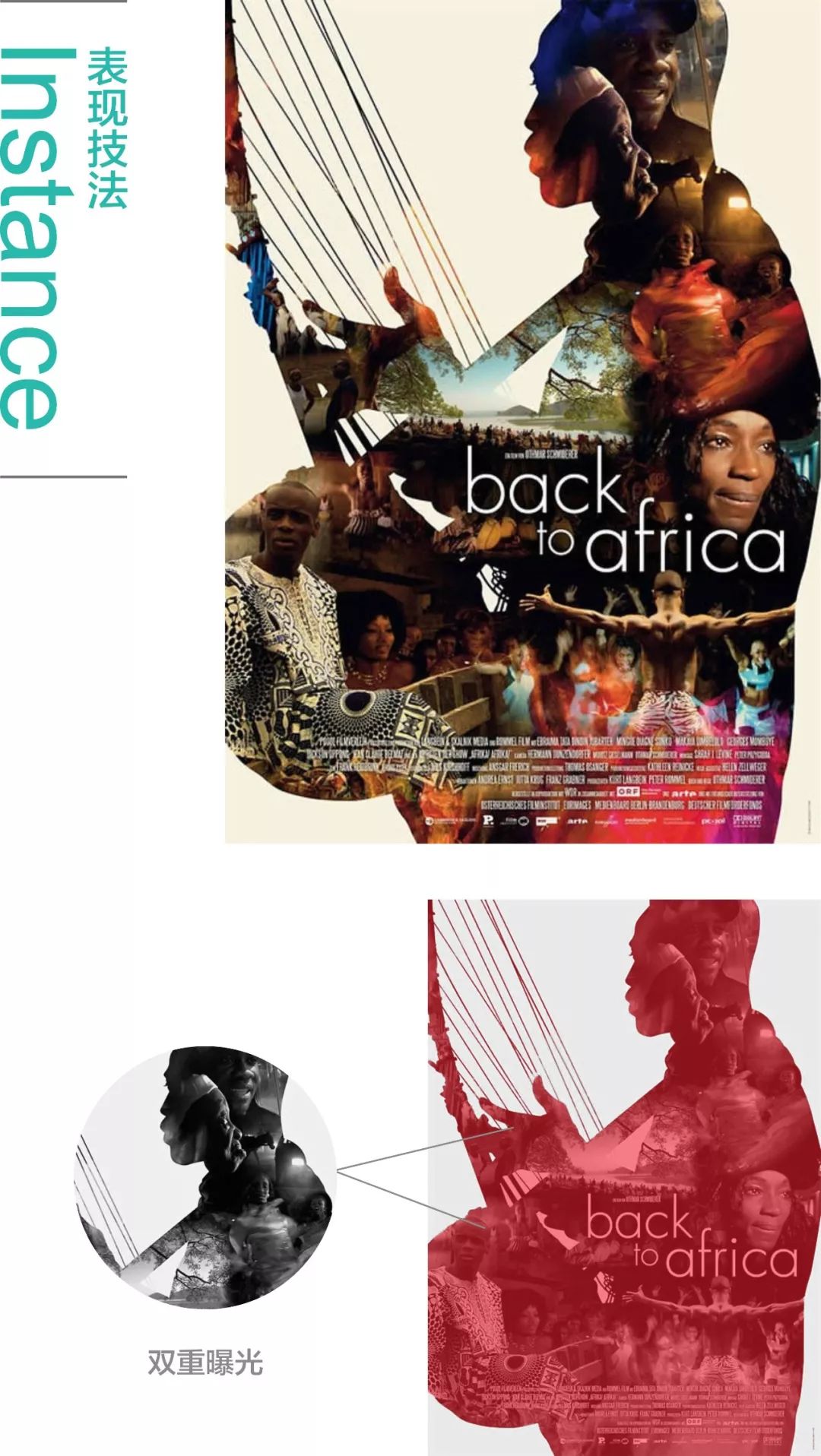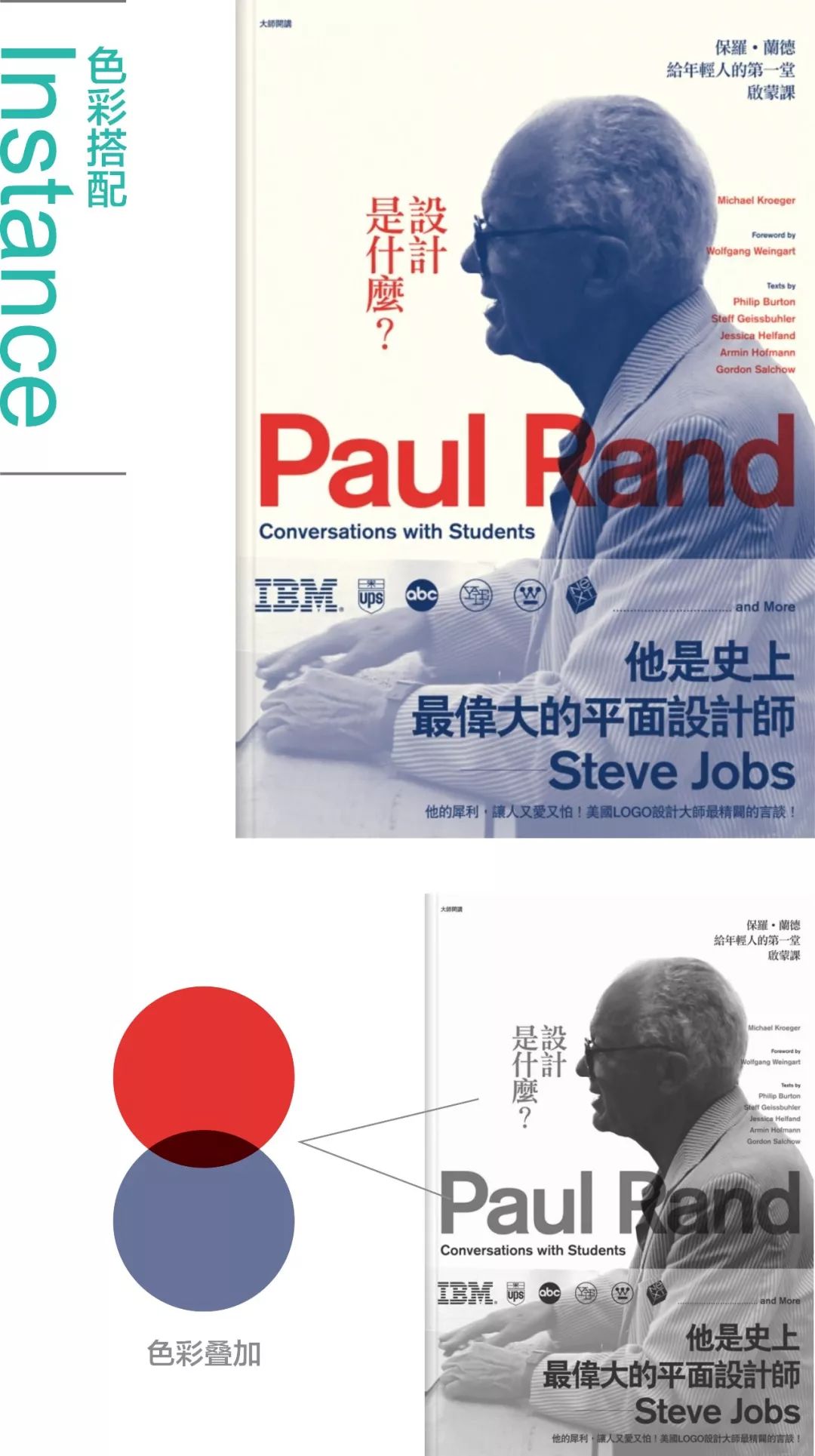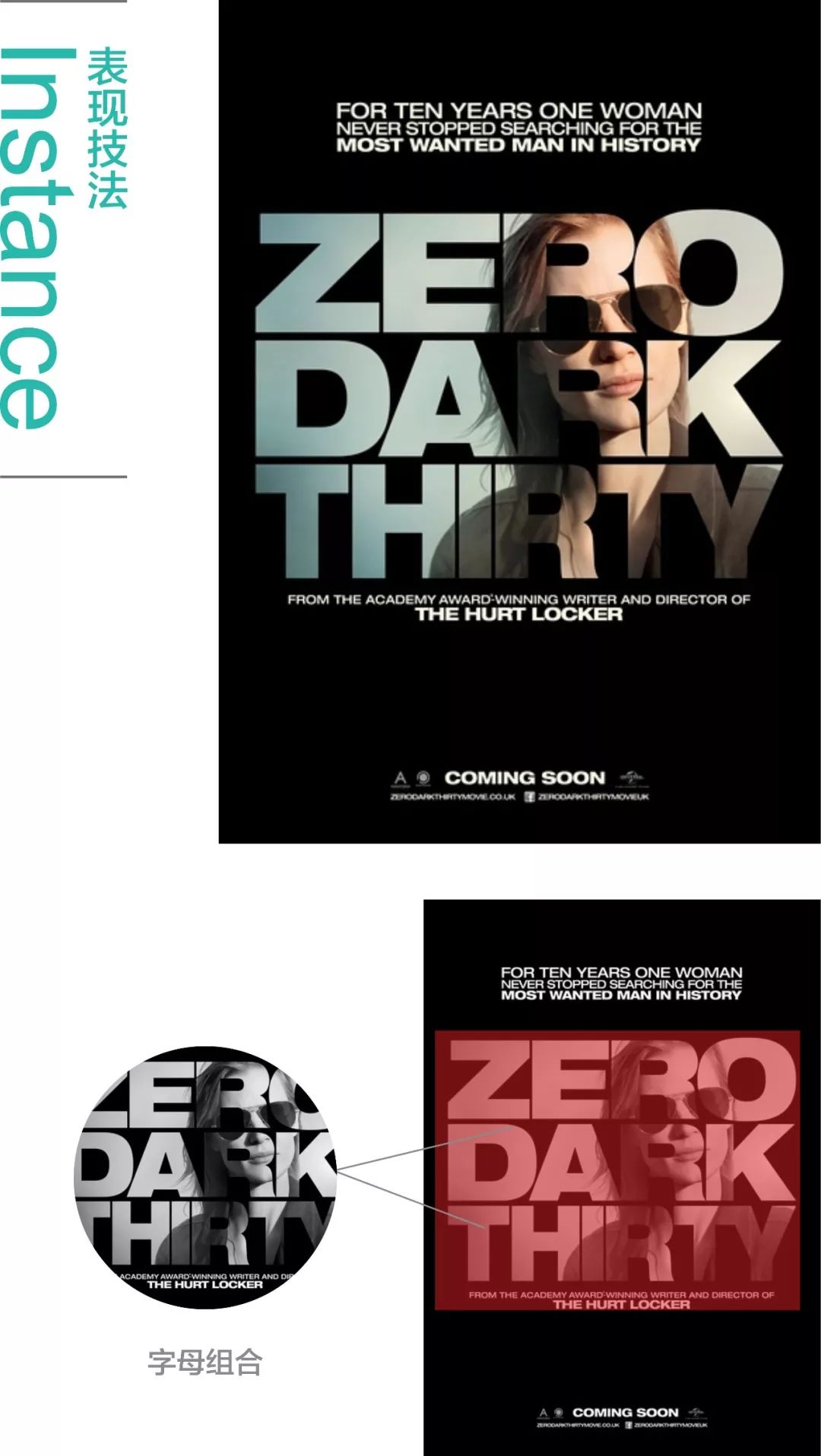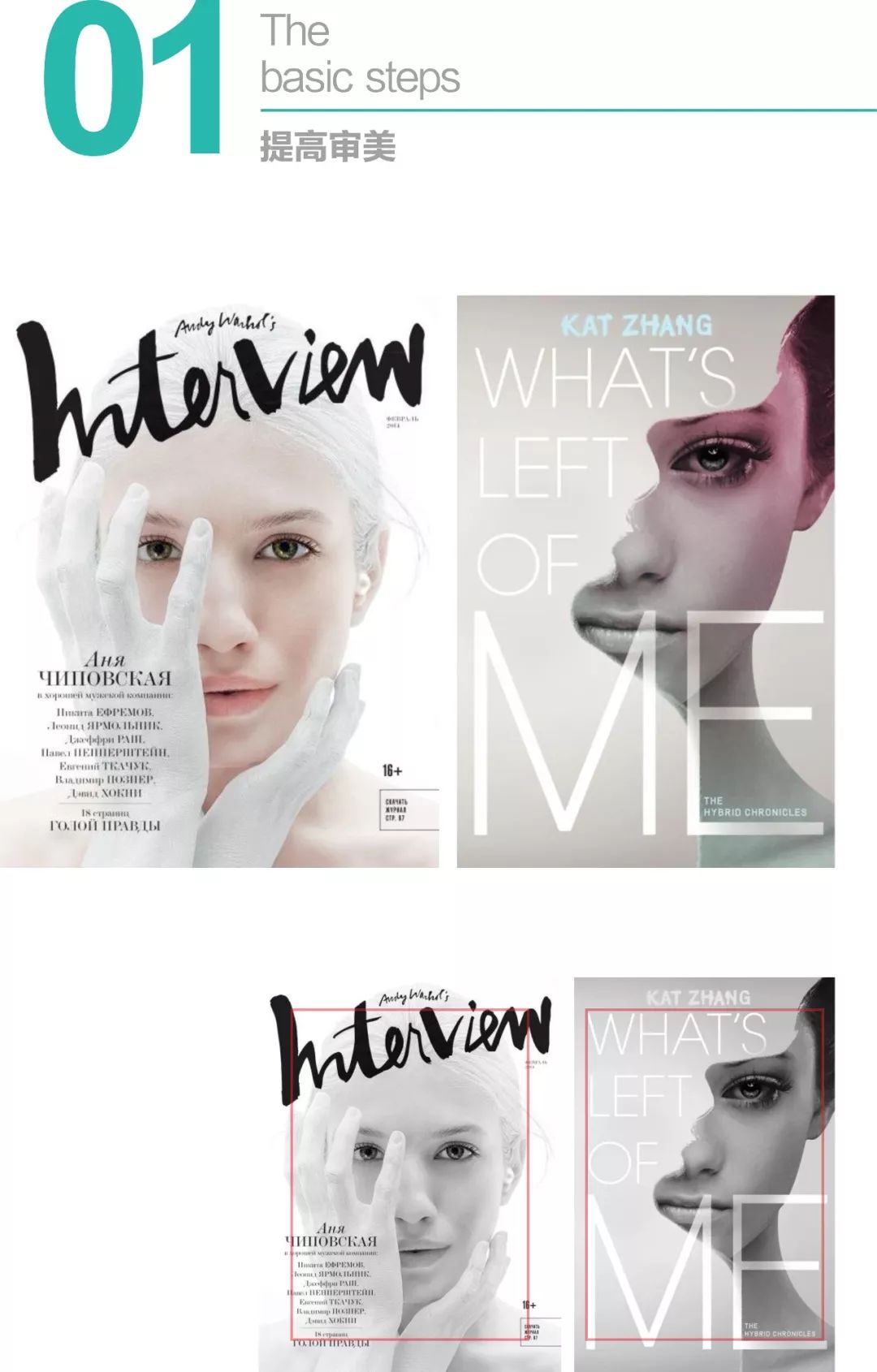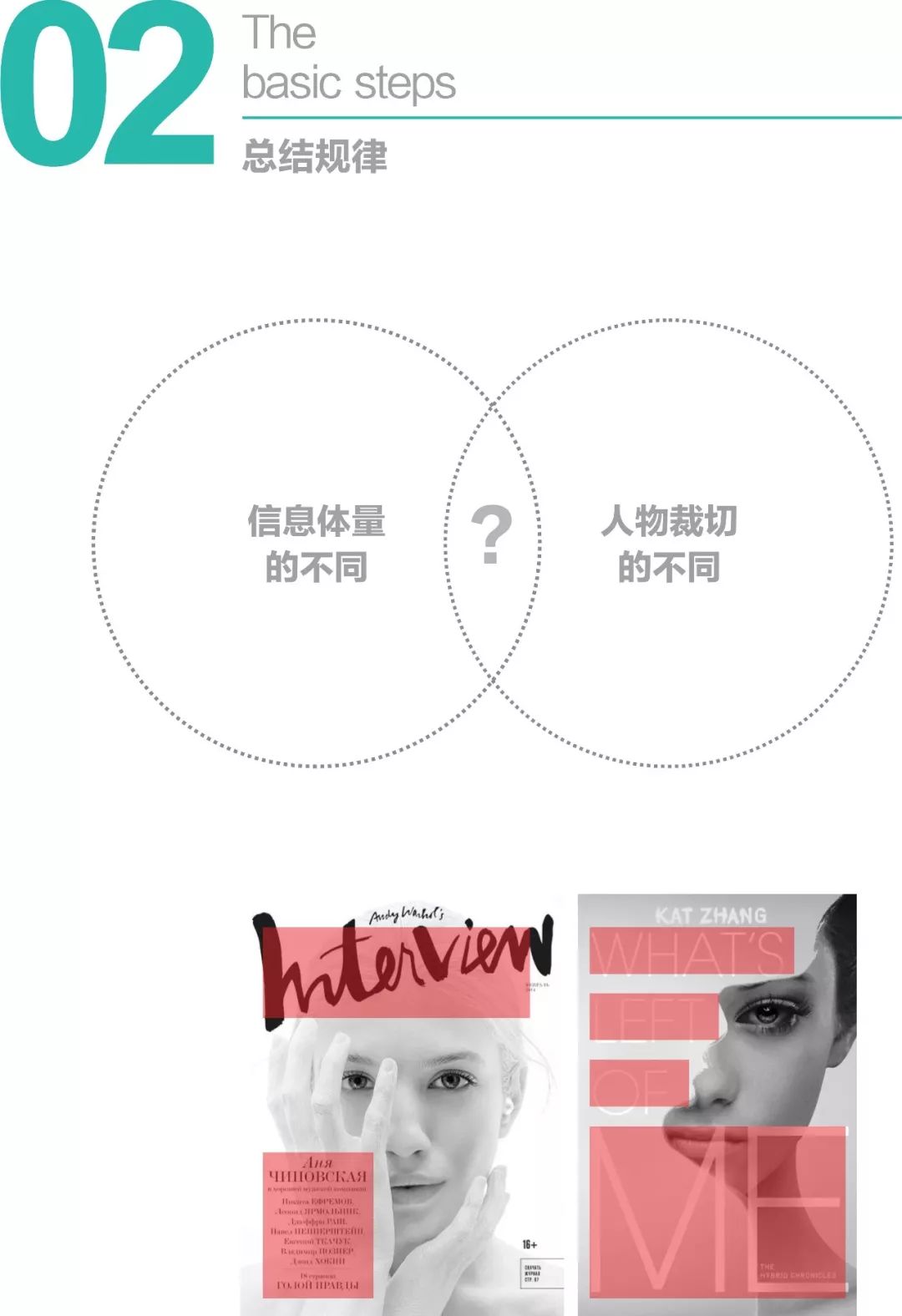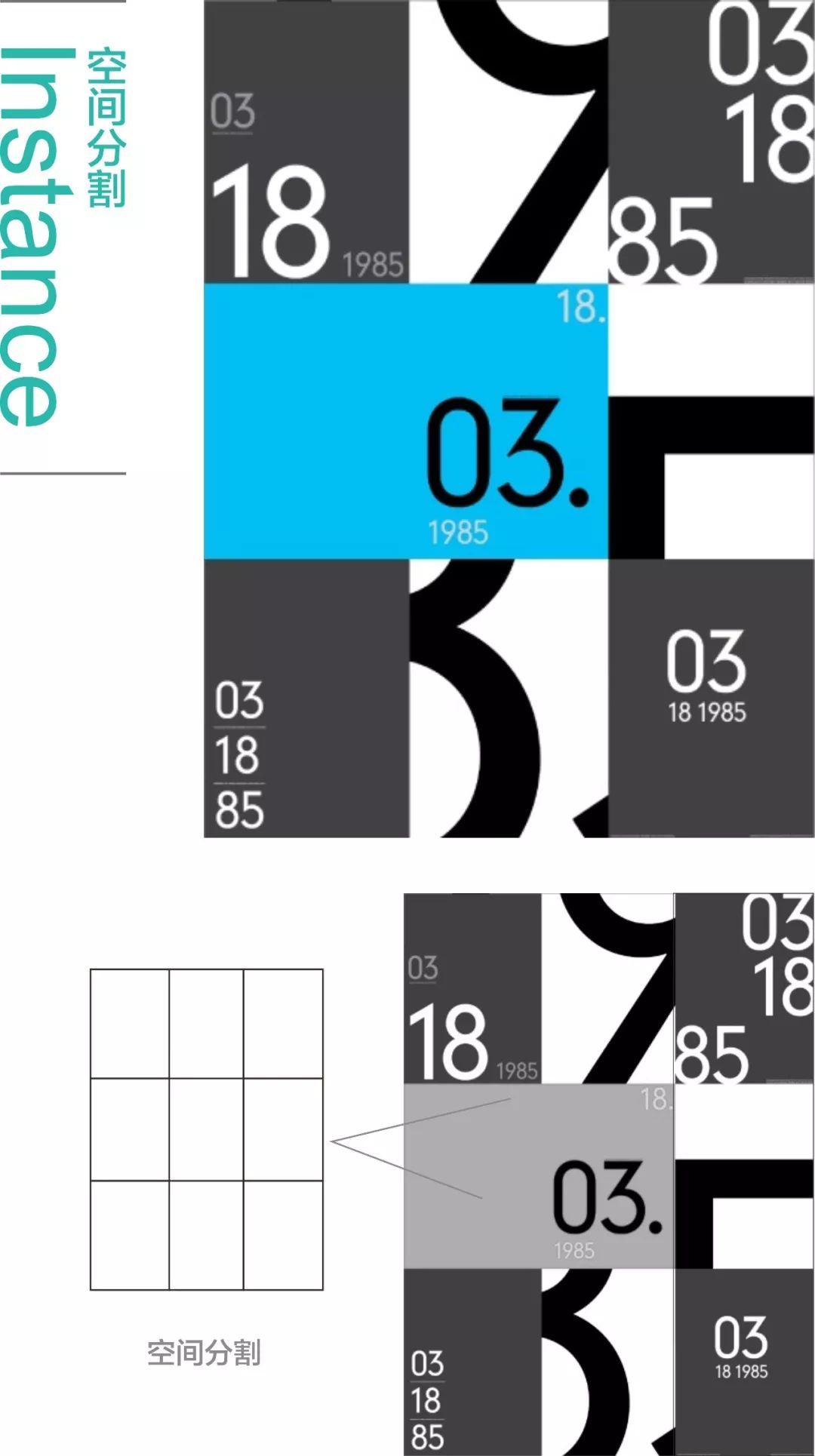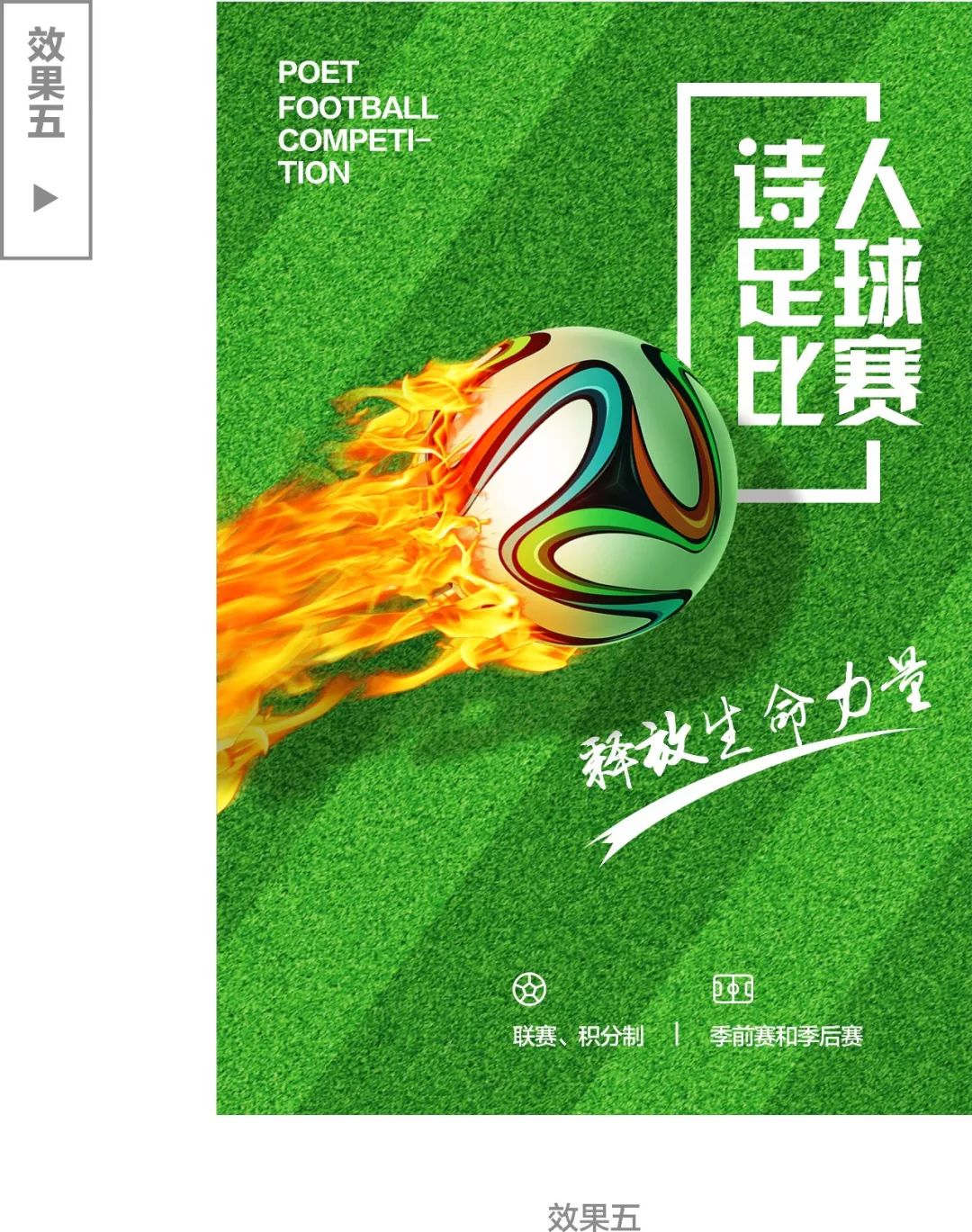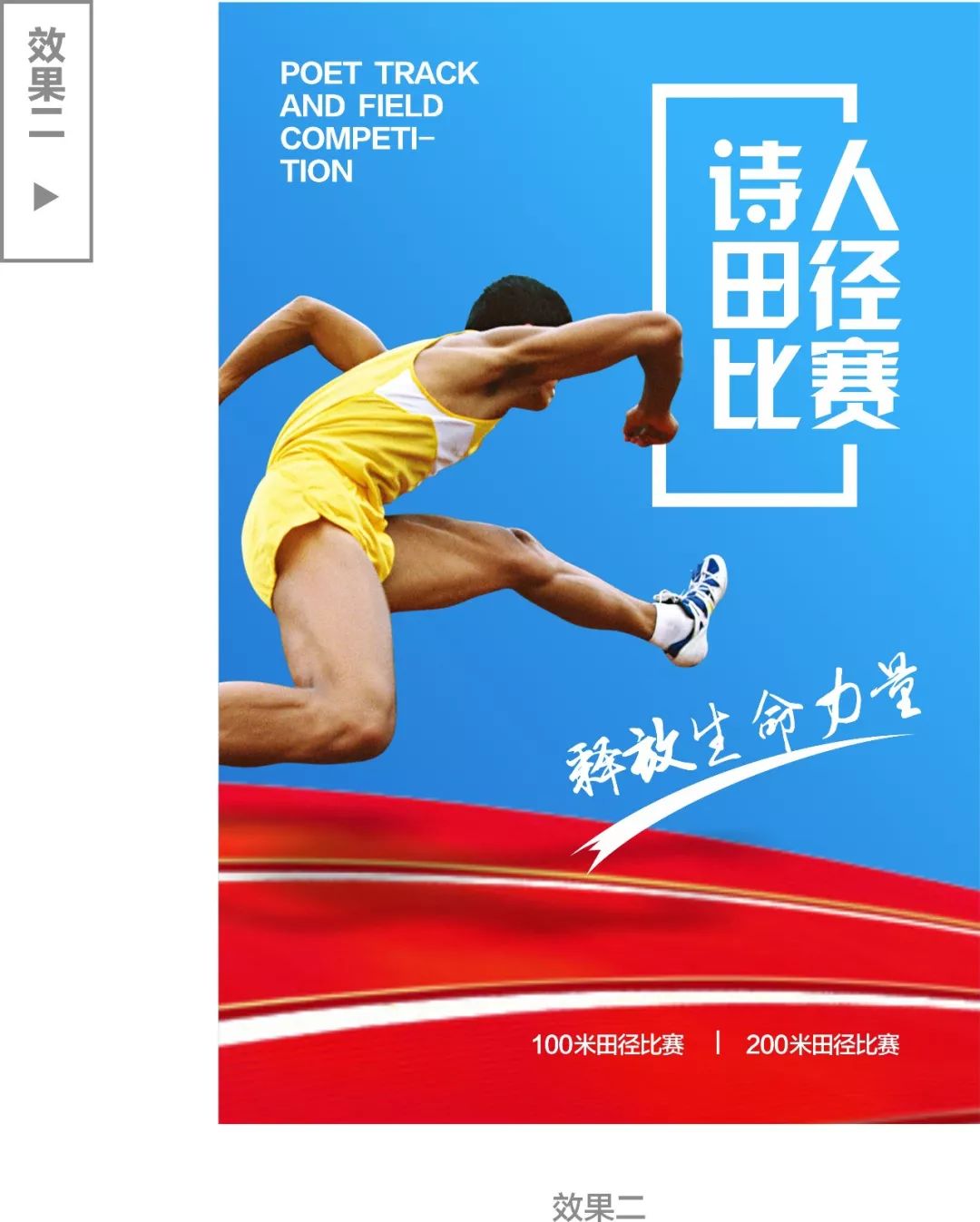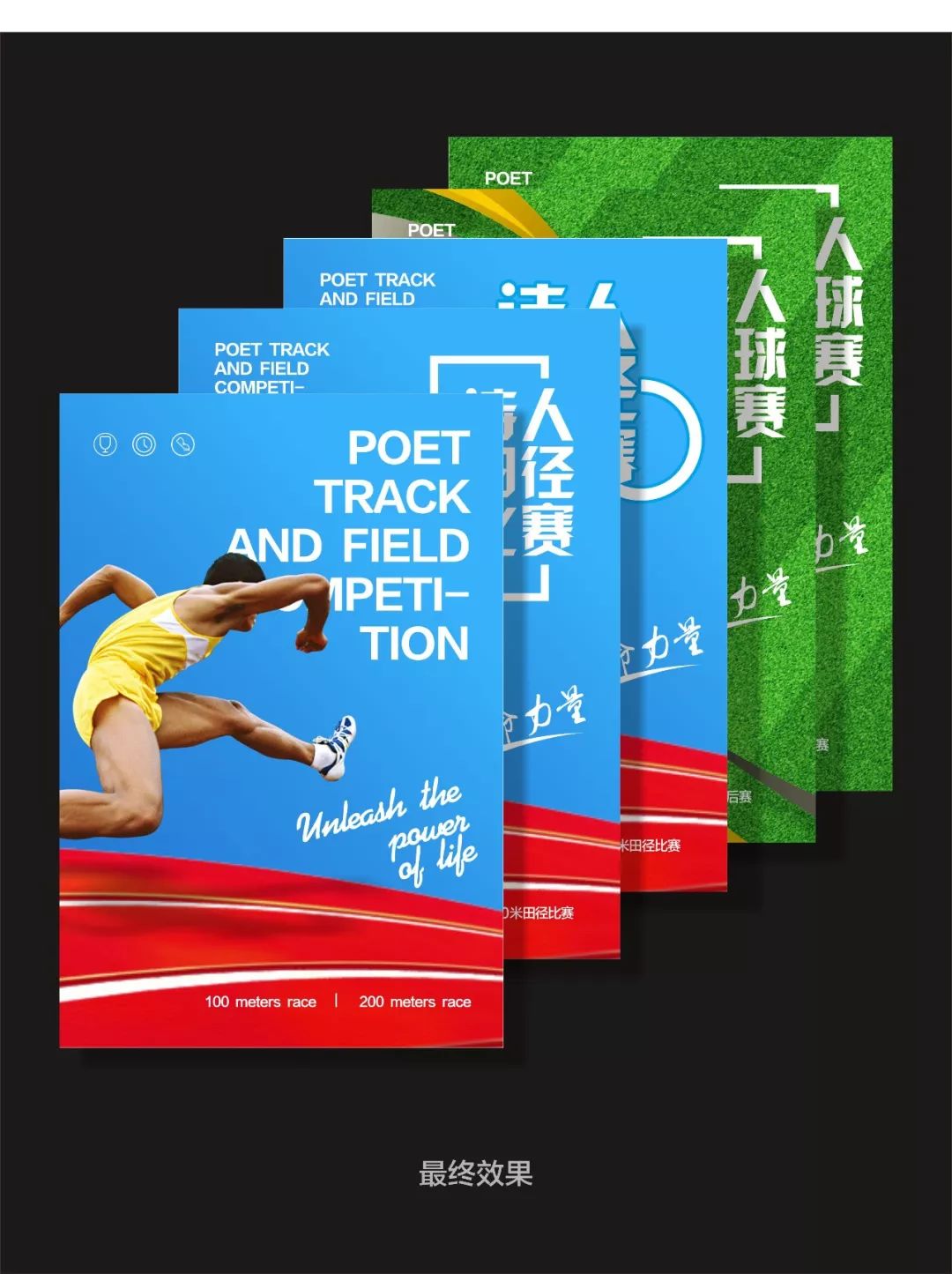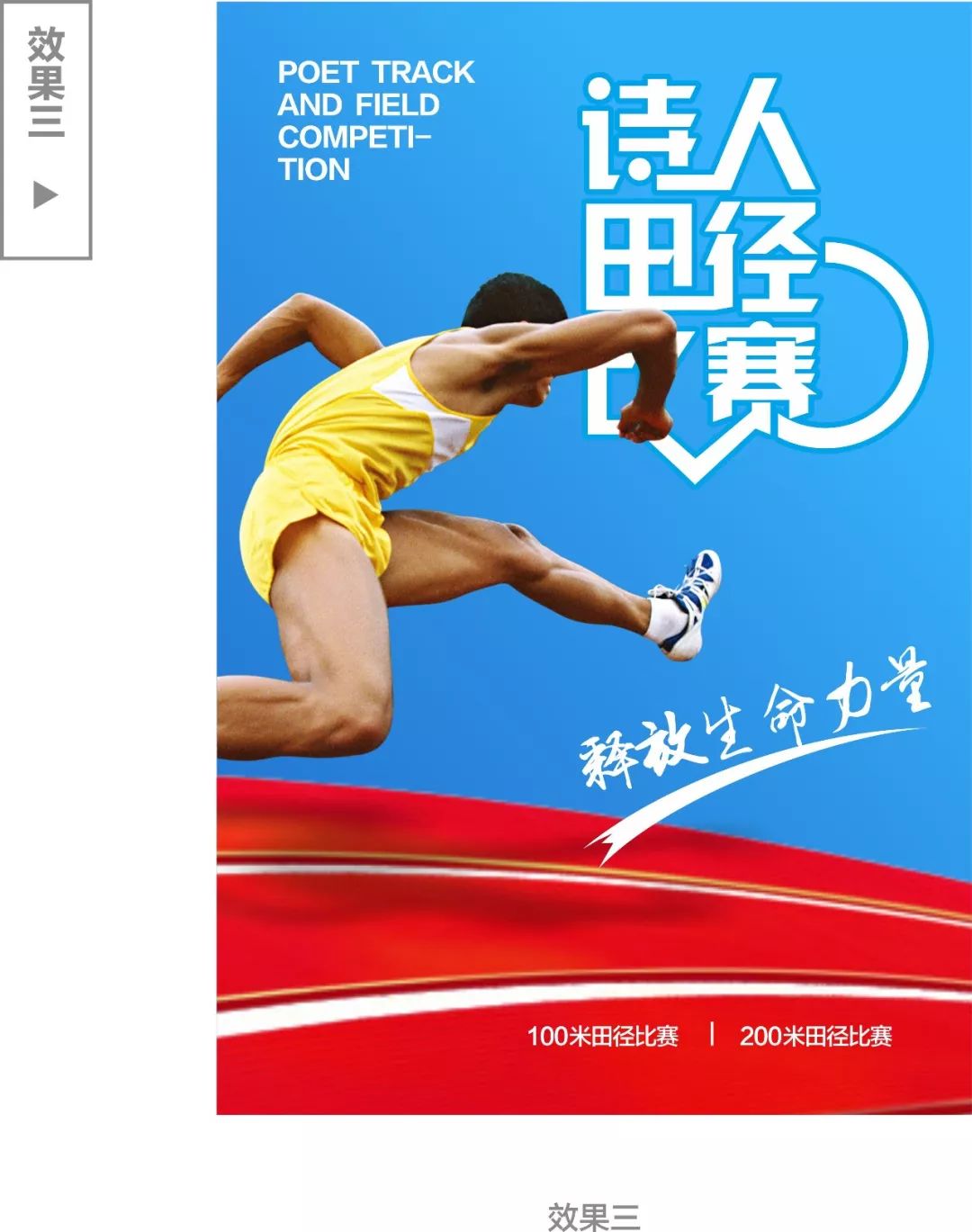
快速掌握设计的临摹诀窍,教你如何设计临摹
前言
对于很多设计师而言,从一开始接触设计就已经对设计本身存在了一定的误解,感觉设计是应该凭空创造而来,没有创意或者说原创的设计都称不上设计,还“看不起”所谓的临摹借鉴,所以直接导致的后果就是自己凭着丰富的想象能力想了好多年,水平却一直原地踏步走;还有的设计师从一开始就是搜集“素材”,大部分时间都浪费在了“素材”上。
所以前期大量的看优秀作品积累灵感是非常必需的,但是如何能够理性的去“临摹”灵感,而不是去走马观花,这就需要对设计作品本身进行分析总结与思考,第一期“临摹专题”我们来探讨其中的诀窍。
学习的两个阶段
寻找相似的作品,将他们进行归类整理也是非常之重要,比如这两张海报在人物主体的安排上比较相似,先采集大量的类似作品提高审美。
然后再去对比他们之间信息的不同安排,总结其规律。比如这两个画面,信息在对齐规则上就不尽相同,是信息体量不同的原因还是其他?这就是一个思考的过程。不断训练,不断强化。
临摹的思路是什么
我们平时其实也看过不少的优秀作品,但是具体怎么临摹,万一临摹的一模一样会不会被客户发现?当然这个想法很明显就是不会临摹,我们要临摹灵感,灵感来源于哪里?
分析一个优秀的作品,首先要从项目气质着手,然后再去分析字体的气质,色彩的搭配,信息的归类,主体的选择,构成的表现手法等。而且我们分析作品要分析看得懂的项目,并且把画面中最主要的特点显现出来。
实例解析
上面的海报将人物置入到英文字母中,采用英文字母与人物内置组合的形式让视觉点变得有趣,这也是上面海报我们需要学习的重要部分。
这个海报的形式更多是在色彩上的搭配,用对比色的搭配手法,撞色效果比较棒,人物图片统一处理成单色蓝,设计感十足,简约而有国际范。色彩搭配巧妙的将画面变得与众不同。
上图海报采用的是主体人物的形象轮廓与其他场景与人物的融合,做出的双重曝光的视觉效果,这种手法在电影海报中经常被用到,同样的在这个海报中是最大的亮点,值得我们去学习。
这个海报更多的是利用色块按照信息的内容将画面分割成若干个空间,每个空间的大小比例都不尽相同,而且在方向上也有一定的对比,当我们碰到信息比较多的时候或者做某些目录时也可以尝试使用。
优秀样例实操
我们在收集作品的时候,千万不要只看不做,学习也是分状态的,尤其是碰到自己比较喜欢的作品一定要动手去尝试临摹着做,从中去分析作品的优点。
上面的海报是骑行运动类的项目,风格上采用的是插画手绘形式,在气质上更偏激情,活力。首先在画面主体的选择上选择了一个比较有张力的透视角度,视觉效果很棒。
色彩搭配上,蓝绿色搭配明黄色,蓝绿色寓意运动的健康与纯净,而明黄则寓意活力与激情,并且属于对比色搭配方式,主题视觉更为醒目。同时背景色采用了渐变形式的蓝绿色,突出场景的空间感。
画面中的字体选用了无衬线体作为主字体,硬朗,力量,简约,在画面的右下角使用了手写体,自由,随性,天然。都准确传达出了运动的项目气质。
临摹思路操演
分析完上面作品的项目气质,色彩搭配,字体选择后我们也尝试着去做一些类似气质的练习,在练习中学会慢慢消化,总结思考,将优秀作品中的优点真正用到我们的作品中,提高自己的学习力,成为一个“会学习”的人。
通过上面作品的分析,我们在网上找到如下三个不同的运动图片,根据三个人的形态可以得知A图更加合适,主体人物张力最大,所以选择A图。
新建一个画布,将图片放置其中,图片小的话视觉效果比较平均,所以将图片放大,利用九宫格形式确定人物的大概位置,这样主体人物的形态趋势就会使画面比较有张力。
尝试使用同类色和互补色进行色彩搭配,同类色(背景黄色)搭配统一性较强,但是视觉感不强烈;互补色(背景蓝色)搭配则色彩碰撞,对比性强烈,表现力更好。
将人物做出投影效果,主体形象更饱满,接着将背景做渐变化处理,背景多了纵深感,相较于纯色背景来说,层次感更好。
将文字信息按照重要性用层级对比的形式编排好(利用大小对比,动静对比,方向对比,疏密对比的对比形式合理安排信息)。
将主标题的位置进行调整,叠压在人物下方,形成前后的空间,人物和主标题之间形成位置上的关联,整体性更强。再为画面背景添加上一个跑道,视觉上更具备空间延续感。
最后添加上和田径运动相关的图标,丰富画面,而且还可以深化项目主题。
做过英文版本后,我们尝试做一款中文版本,将文字信息都替换成中文形式,发现主标题显得过于单薄,将主标题由一行变成三行,由原来的方正兰亭大黑换成迷你简菱心字体(字型更为更有力量感)。
虽然主标题进行了行数编排和字体置换,但是和人物的关系还不够,所以利用几何线框与人物建立了位置上的关系,整体性体现出来。“释放生命力量”也手绘一个向上的不规则图形组合起来。
最后在左上角部分用上主标题的英文作为装饰点题,弥补空间,丰富画面。
当然,我们也可以将主标题进行字体设计,利用笔画同构,利用几何形与之组合形成更丰富的视觉点。
将设计好的标题放置在画面中,这样主标题就可以将比例放大,占据更大的视觉空间,同时做出一层浅浅的描边效果,效果亦不错。
上面完成稿是以人物作为主体去深入刻画,那么我们如果换成其他形态的事物,是否也适用呢,下面我们将人物A替换成足球B。
我们将原来的人物去掉,置换成找到的足球B,发现缺少了一种冲击力与动感,接着用发散的趋势将足球环绕起来,整个足球主体的动感与视觉张力就表现了出来。
对于足球而言,背景的颜色我们首先可以联想到绿茵草地,填充成渐变绿色,但是效果会显得平,怎么能够显得立体呢?当将绿茵草地作为背景时效果就会很丰富,最后做出投影让足球更立体。
为了进一步使画面变得更丰富,最后添加上跟足球相关的图标,起到点的提示作用,而且又再次丰富了画面的细节。而且背景也做了切斜处理,烘托出一种运动的速度感。
将原来的A足球替换成更丰富的B足球,B足球有种少林足球的感觉,视觉效果更丰富夸张。
将原来版面中的足球替换成新的足球主体,为了和画面中的足球场背景相匹配,将足球逆时针旋转一个角度,并做出投影效果,更为立体与真实。
第五种效果完成稿,效果更为真实夸张。其实做提案的时候每个客户都有不同的审美,有的更喜欢夸张,有的喜欢平稳。不能说哪个画面一定最合适。
总结
第一期关于如何正确的掌握“临摹诀窍”的思路就分析到这里,希望在实际的学习工作中我们能够灵活变通,知道从哪些点入手,积累总结,不断的提高自己的水平。
设计虽没有近路,但可以少走弯路。